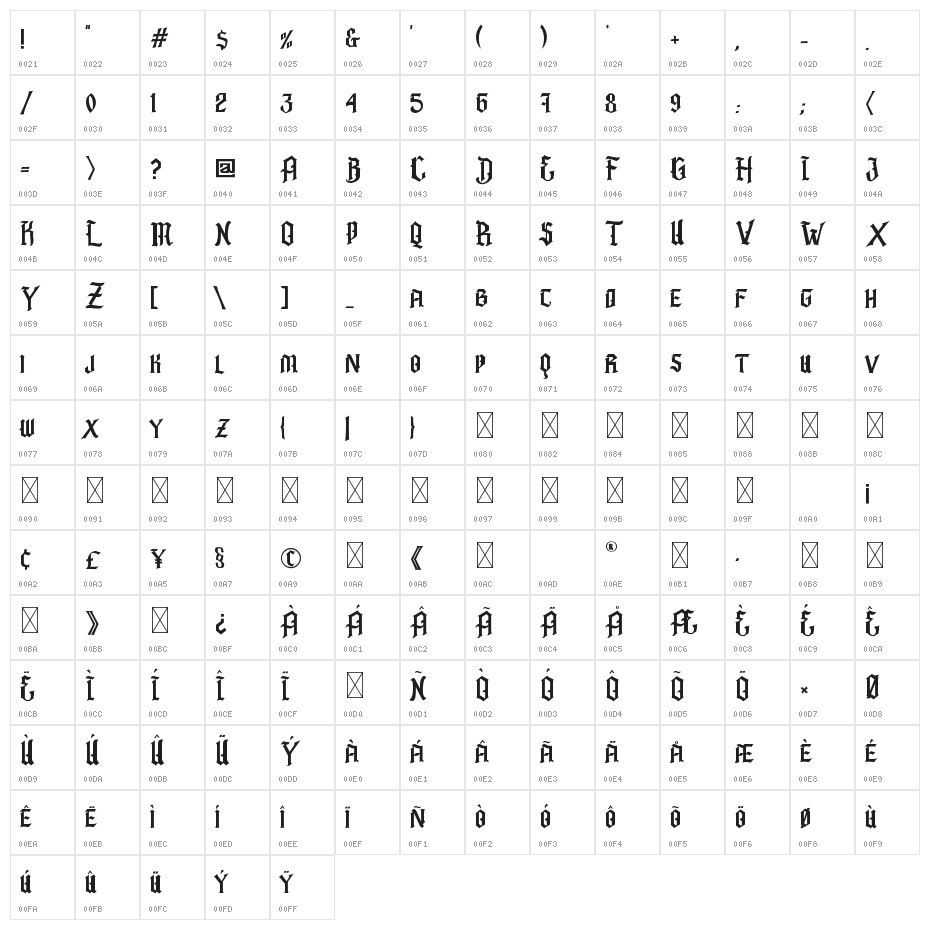
Barbatos Regular Font
| Gesamtstil | Gothic, Medieval |
| Anwendungsfall | Headlines, Logos, Decorative text |
| Vorgeschlagene Projekte | Ideal for projects requiring a medieval or fantasy theme, such as book covers, posters, or themed event invitations. |